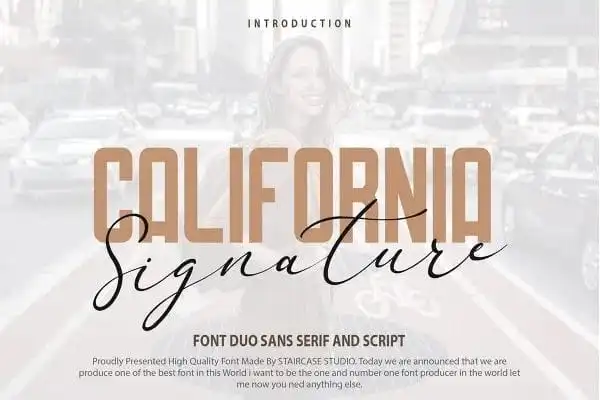
California Signature Font Duo – Download Grátis
A California Signature Font Duo é uma fusão atraente entre uma tipografia script e uma sans serif, inspirada nas combinações modernas de assinatura e tipo pura que vemos no dia a dia das grandes marcas e designers digitais. Esta fonte foi criada pelo talentoso designer Staircase Studio. Com seu estilo casual ou sofisticado, você pode criar cabeçalhos elegantemente clássicos ou textos elegantes. É perfeito para qualquer aplicação de personal branding, publicidade ou criação de design gráfico. A combinação única do tipo de assinatura e o swash font adicional oferecem uma variedade infinita de opções para seus projetos. Esta dupla é ideal tanto para aqueles que buscam algo mais tradicional e elegante quanto para quem busca um visual mais moderno e criativo. O uso desta fonte trará a sua criação ao próximo nível, seja em uma campanha publicitária ou em seu próprio website de personal branding.